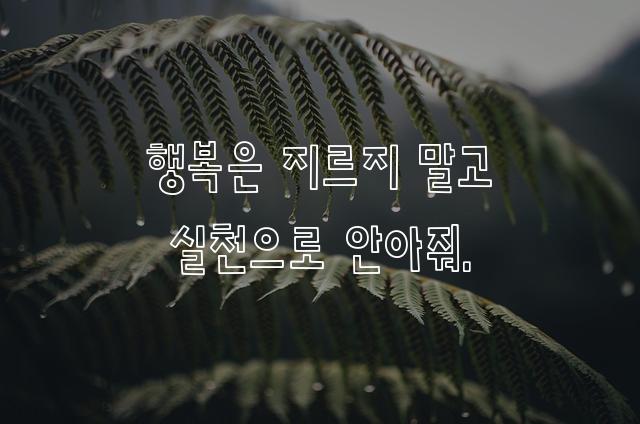
피플퍼스트자립체는 피플퍼스트성북센터에서 제작한 한글 폰트로, 펜을 사용한 듯한 자유롭고 유연한 필기체가 특징입니다. 이 폰트는 따뜻한 감성을 전달하며, 친근감을 느끼게 해줍니다.
펜/붓터치 계열의 생김새를 가지고 있으며
프레젠테이션, 보고서/문서, 출판물 제목 등에서 자주 활용되며, 효과적인 메시지 전달에 적합합니다.
이 폰트는 출판/미디어, 공공/정부, 금융/비즈니스 분야에 잘 어울리며,
신뢰감, 명확한, 전문적인 느낌을 담고 있는 것이 특징입니다.
이 폰트와 유사한 폰트로는 한나체, 바른펜체, 마포금빛나루체 등이 있어요. 함께 비교해 보시면 좋습니다!